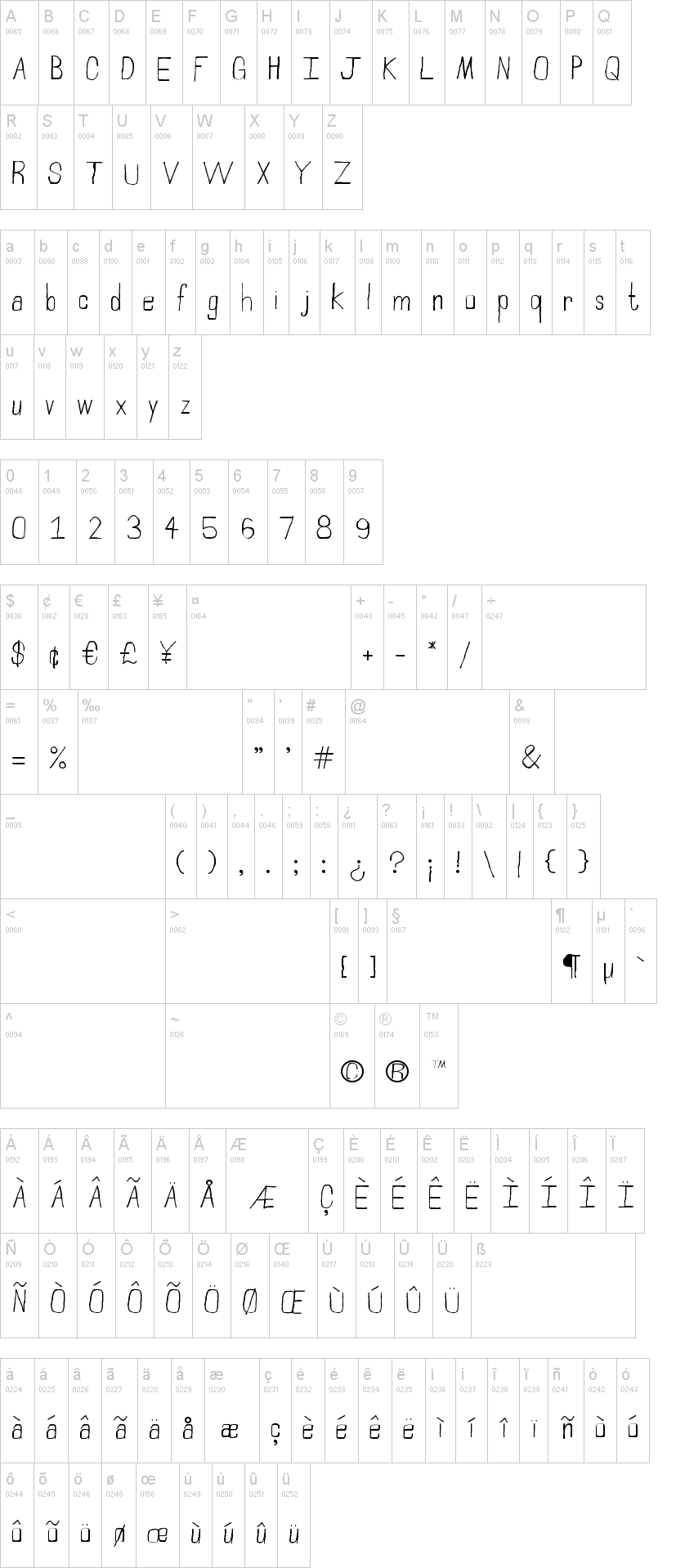
Northampton字体是一款古典的英式手写体字体,它的特点是字体的笔画清晰,结构简洁,曲线流畅,而且字体的比例也很适中,使用它可以让文字看起来更加精致大方。它适用于各种类型的文字,特别是适合用在报纸、杂志、书籍及其他出版物上。内容介绍
Northampton是一款非常不错的手写艺术字体,具有很好的视觉感,适合于文化类的宣传设计、商业类品牌的广告和产品包装设计以及个性化文字排版等较多场景。